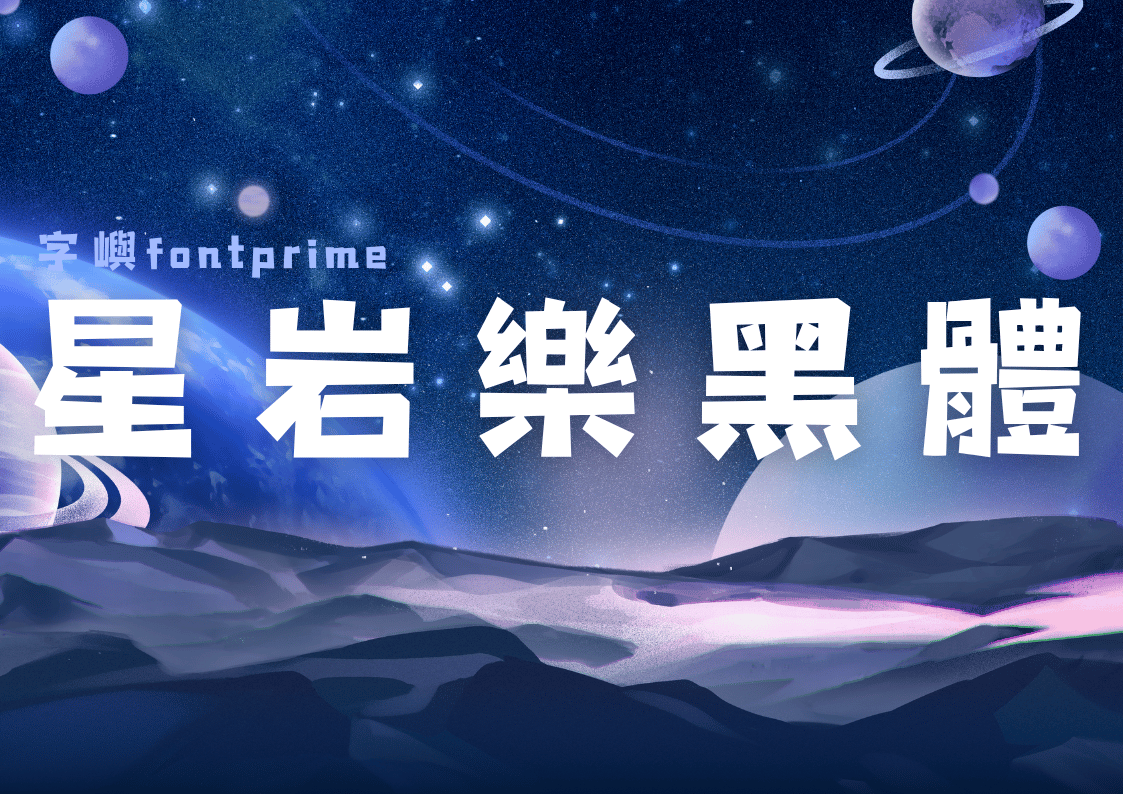
字嶼星岩樂黑體TC
字嶼星岩樂黑體 TC:兼具力量與個性的字體新體驗
在字體的豐富王國裡,每一款字體都像一種獨特的藝術表達,承載著不同的情感與風格。字嶼星岩樂黑體 TC 便是這樣一款充滿力量感與個性的字體,它宛如岩石般堅毅,又似星辰般閃耀,為各類設計作品帶來強烈的視覺衝擊與獨特的藝術氣息,成為設計師們打造個性化作品時的得力夥伴。
風格:剛勁有力,個性鮮明
字嶼星岩樂黑體 TC 的風格極具辨識度,給人第一感覺就是剛勁有力。其筆畫宛如被精心雕琢的岩石,每一笔都充滿了力量,展現出堅毅不拔的氣質。
從字形結構來看,字嶼星岩樂黑體 TC 方正飽滿,間架結構穩固。無論是單字展示還是通篇排版,都能展現出強烈的視覺張力。它的剛勁與個性,使其既適合表達堅毅、果敢的主題,又能為時尚、前衛的設計增添獨特的韻味,是一款風格多變且充滿力量的字體。
適用場景:多領域的個性之選
- 音樂演出宣傳物料
- 在音樂演出領域,字嶼星岩樂黑體 TC 可謂是絕佳的宣傳助力。無論是搖滾音樂節的海報、金屬樂隊的演唱會門票,還是獨立音樂人的新專輯封面,使用這款字體書寫演出名稱、藝人名稱,都能瞬間抓住人們的目光。它剛勁有力的筆畫與音樂的強烈節奏感相得益彰,仿佛能讓人聽到字裡行间的鼓點與嘶吼,極大地增強了宣傳物料的感染力,吸引更多音樂愛好者前來觀看演出、購買專輯。
- 運動品牌推廣設計
- 運動品牌往往需要傳達出活力、挑戰、堅持的精神,字嶼星岩樂黑體 TC 恰好能完美詮釋這些內涵。在運動品牌的廣告海報上,用該字體書寫品牌口號,如「挑戰極限,超越自我」,能讓口號更具震撼力,激發人們的運動熱情。運動服裝的吊牌、運動裝備的包裝上使用這款字體,也能與產品的功能性和運動屬性相匹配,提升品牌的個性化形象,吸引追求時尚與個性的運動愛好者。
- 戶外探險活動策劃
- 戶外探險活動充滿了挑戰與未知,需要一款能展現其冒險精神的字體,字嶼星岩樂黑體 TC 便是不二之選。在探險活動的招募海報、行程手冊上,用該字體書寫活動主題,如「征服高山,探索秘境」,能很好地傳達出活動的艱險與刺激,吸引那些熱愛冒險、勇於挑戰的人們參與。活動現場的指示牌、紀念品上使用這款字體,也能與戶外探險的氛圍相融合,增強活動的整體感染力。
- 遊戲角色與場景設計
- 在遊戲行業中,尤其是動作類、冒險類遊戲,字嶼星岩樂黑體 TC 能為遊戲角色命名、場景標示等設計增添獨特的魅力。遊戲角色的名字用這款字體呈現,能凸顯角色的性格與實力,如勇猛的戰士、神秘的刺客等;遊戲場景中的標示,如「危險區域」「寶藏地點」,使用該字體能營造出緊張刺激的遊戲氛圍,增強玩家的代入感,讓玩家在遊戲世界中體驗到更強的視覺衝擊與沉浸感。
字元與編碼:豐富齊全,靈活應用
字嶼星岩樂黑體 TC 擁有豐富的字元庫,以台語常用標准漢字為標准,參考jf7000字集,包括注音符號、歐文字符、阿拉伯數字和標點符號,總字符約7640字以上。涵蓋了日常生活和設計中常用的漢字、字母、數字以及各類標點符號。
無論是面向大眾的設計作品,還是涉及到國際交流、英文元素的設計專案,字嶼星岩樂黑體 TC 都能提供字元支持。(目前字元集先以台語常用標準字為基礎建置,後續會逐步規劃擴充在地化用字,期待未來能更完整地服務臺語書寫需求。)在處理英文單詞或數字信息時,其字母和數字的設計與漢字相互呼應,保證了整體排版的和諧統一。豐富的字元資源讓設計師在創作過程中可以更加專注於發揮創意,靈活地運用這款字體打造出各種獨具匠心的設計作品。
字嶼星岩樂黑體 TC 以其剛勁有力的風格、廣泛的適用場景、豐富的字元資源和嚴格的版權保護,成為字體領域中一款備受矚目的個性字體。它不僅能為設計作品帶來強烈的視覺衝擊,還能傳達出獨特的情感與態度,是各類追求個性與力量感的設計項目的理想選擇。無論你是專業設計師,還是有設計需求的企業或個人,字嶼星岩樂黑體 TC 都值得一試,讓它為你的作品注入獨特的力量與個性,更好地吸引受眾的目光。